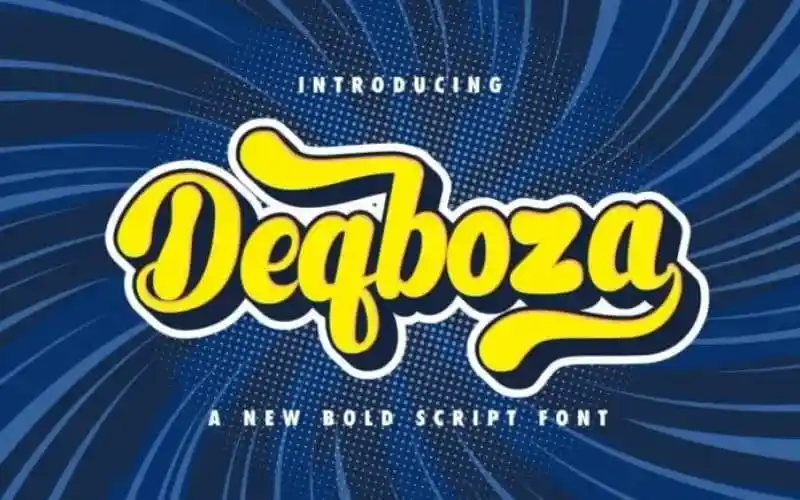
Deqboza Script Font – Fonte Grátis
Deqboza Script Font
Introduzimos a Deqboza Script Font, uma tipografia de estilo script com um design envolvente. A melodia dos traços é inspirada no desenho com um pen aquarela. Além disso, adicionamos uma natural pressão para reforçar o sentimento suave e fluido. Deqboza Script Font será expandida como família de fontes, oferecendo diferentes pesos e estilos – incluindo curvaturas, redondezas e um estilo vintage único. Este recurso perfeito para marca é ideal para os mais criativos ideias, tornando-as ainda mais vibrantes. Esta tipografia foi desenvolvida pela 99designs e se destaca por sua versatilidade e beleza natural. Ela traz vida aos seus projetos de criação, tornando-os ainda mais imersivos e atraentes, seja para branding ou qualquer outra aplicação visual que você possa imaginar.